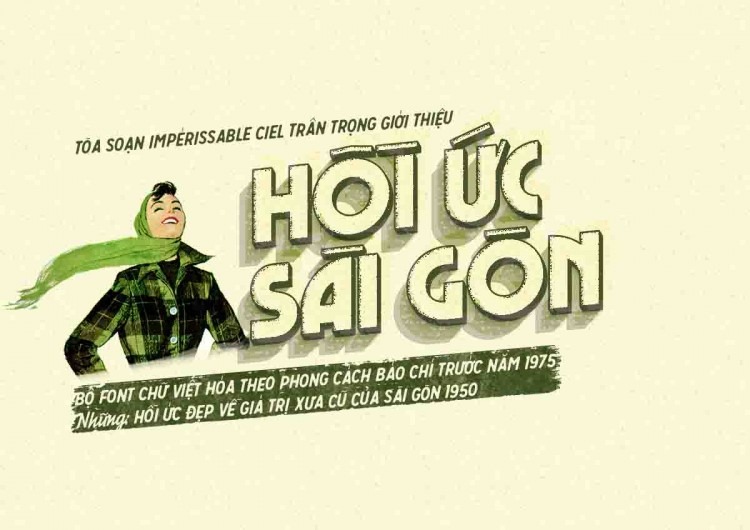
Font Việt hoá iCiel BCLodestone là một font không chân, font hồi ức cũ, font vintage tuyệt đẹp. Font được đông đảo người dùng tại Việt Nam ưa chuộng.
Font Việt hoá iCiel BCLodestone